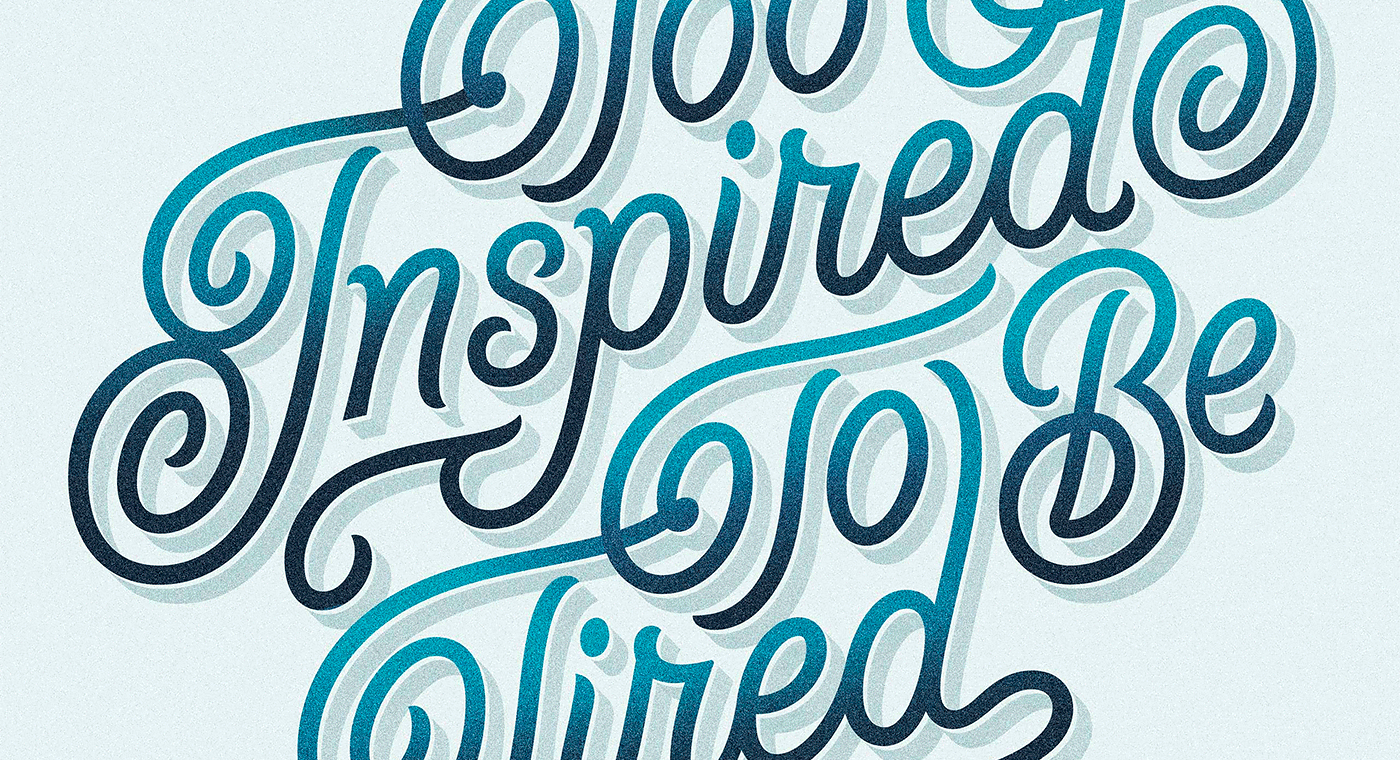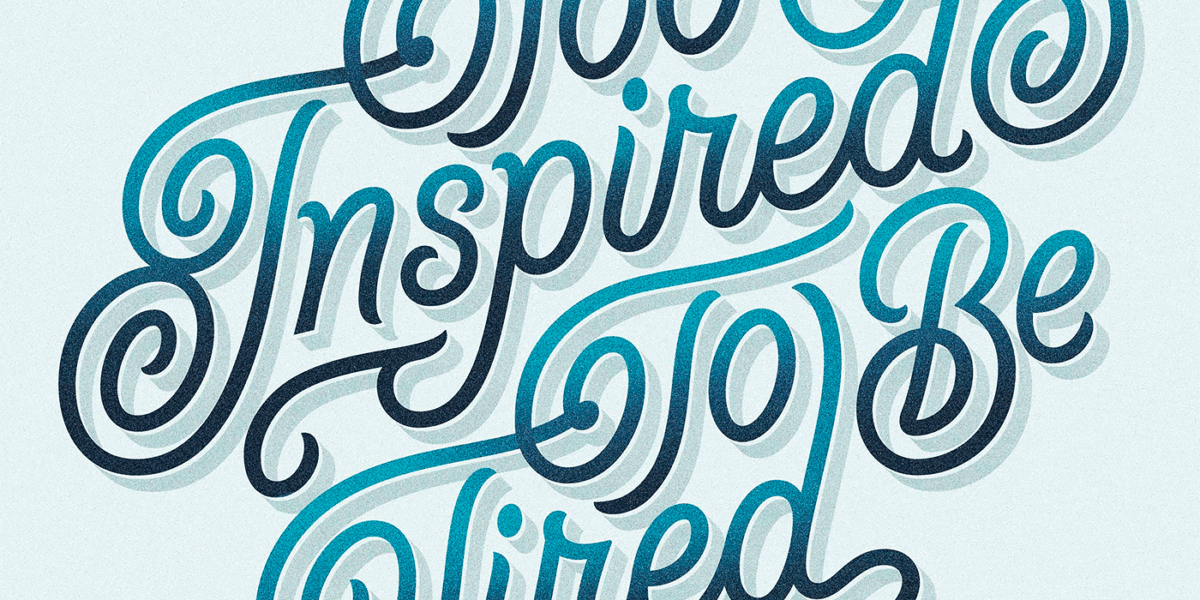
Série criativa de tipografias únicas e modernas para você se inspirar
O desenhista e ilustrador Dan Forster criou uma série incrível de tipografias personalizadas.
Ele tem mais de 20 anos de experiência na área, e sempre colocou em prática a sua ideia de como as tipografias podem criar uma identidade única e expressiva.
Usando toda a sua experiência e talento, ele desenhou lindíssimas letras com design único e moderno para usar em seus trabalhos e mostrar como as tipografias transformam completamente um projeto.
Confira abaixo algumas criações criativas do desenhista para você se inspirar.